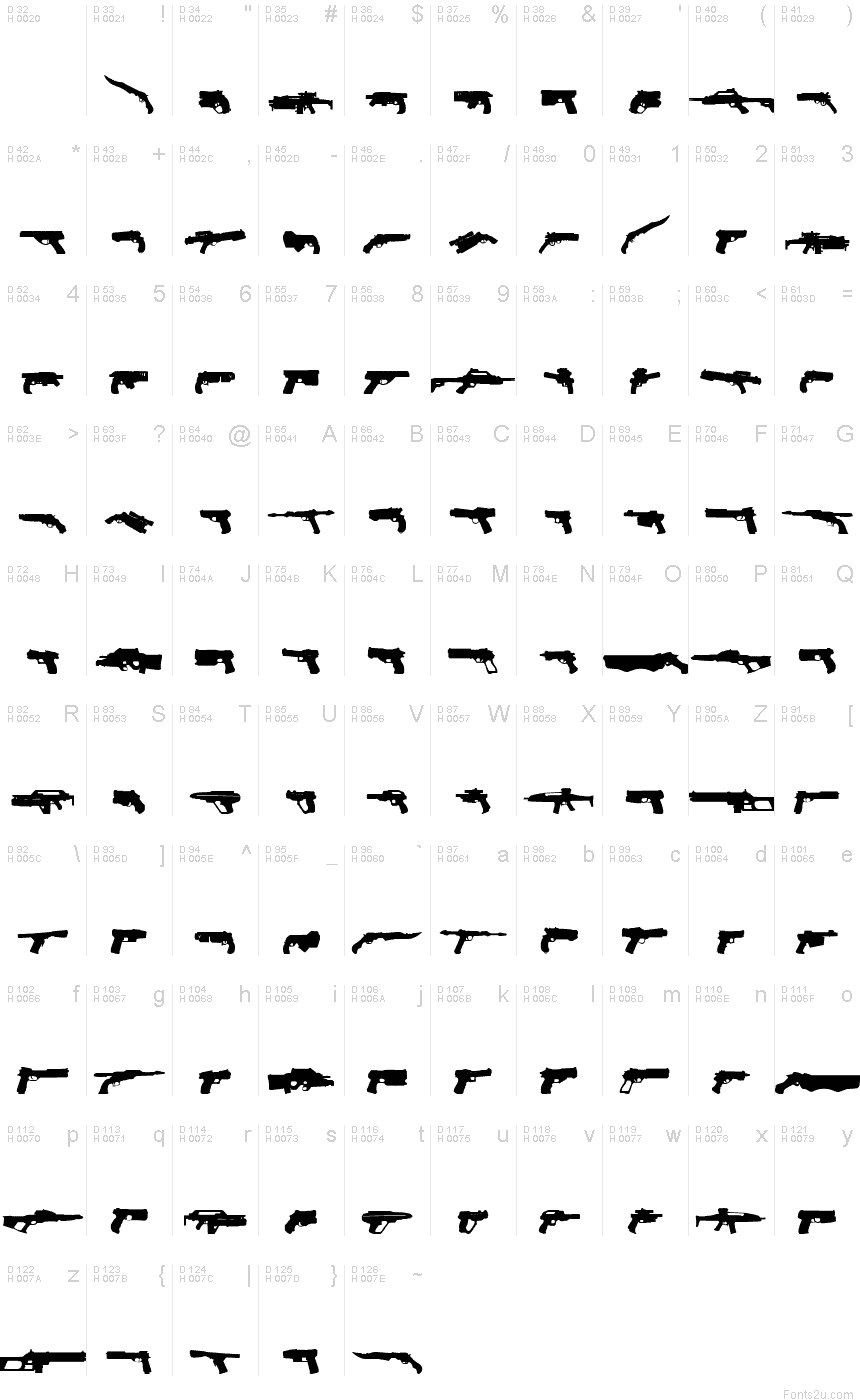
2nd Amendment 2050, von Iconian Fonts, ist eine kostenlose Dingbat-Schrift, die aus markanten, seitlichen Silhouetten von Pistolen und Langwaffen besteht. Das 2009 veröffentlichte Set besticht durch seine prägnante, grafische Bildsprache; mit einer Vielfalt an Griffen, Abzügen, Läufen und Visierprofilen entsteht ein kompaktes Arsenal an Symbolen.
Diese kostenlose Schrift eignet sich hervorragend für Protestplakate, redaktionelle Layouts, Tabletop-Spielmaterialien und Verpackungen im Taktik-Stil. Sie funktioniert am besten bei kurzen Texten wie Titelkarten oder Abzeichen, wo die massiven Waffenformen ohne zusätzliche Details für sich selbst sprechen.